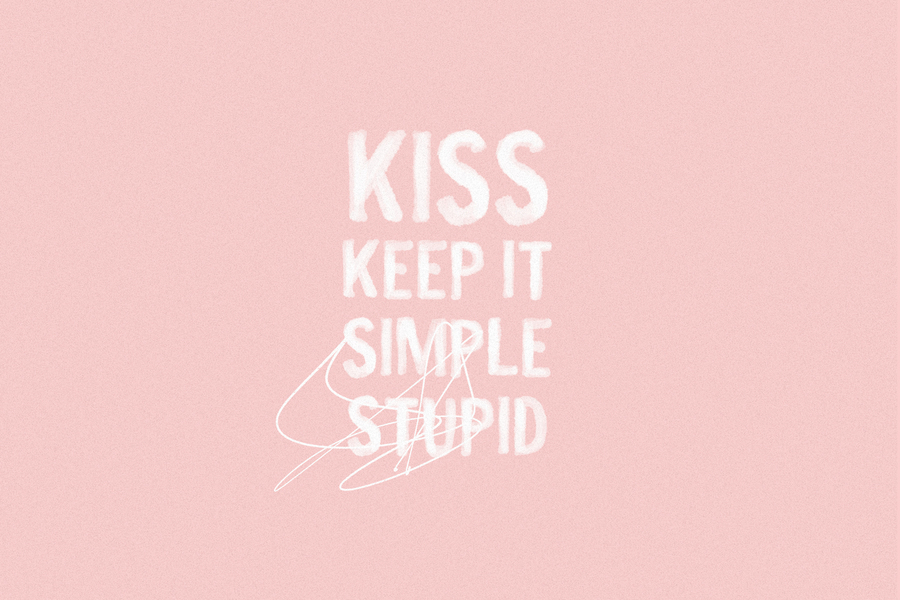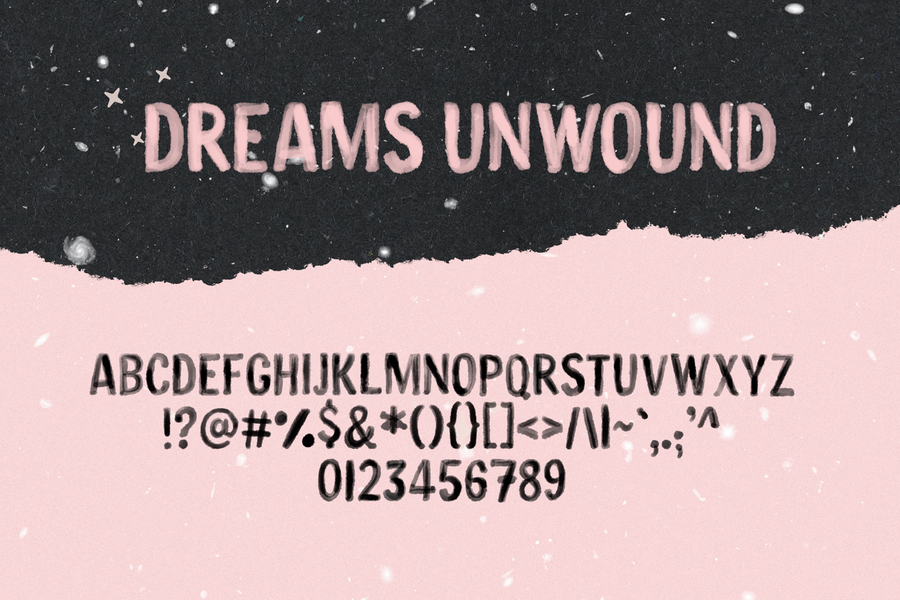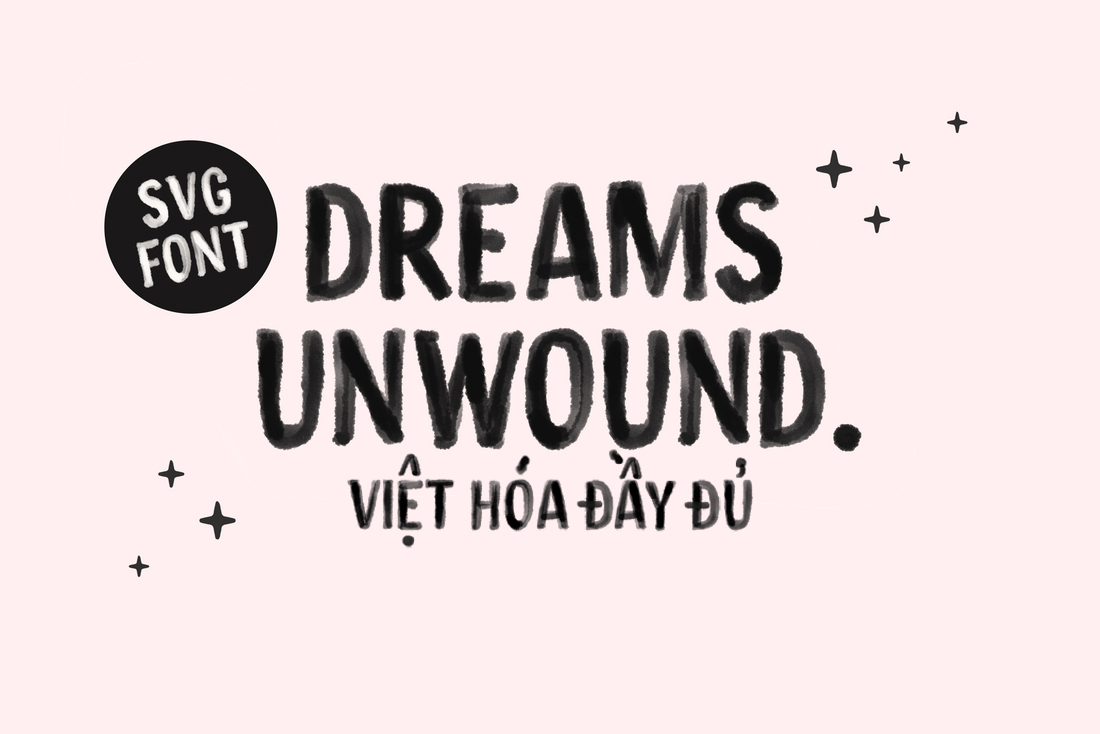
Font Dreams Unwound Việt Hóa là một phông chữ SVG sans serif màu nước hoàn toàn được viết hoa. Bạn có thể sử dụng để thiết kế áp phích, phương tiện truyền thông xã hội, xây dựng thương hiệu, thiết kế bao bì, bản in, hàng hóa hay bất kỳ dự án nào cần sự sáng tạo và chuyên nghiệp.
Phông chữ Dreams Unwound có dạng chữ thường và chữ nghiêng.